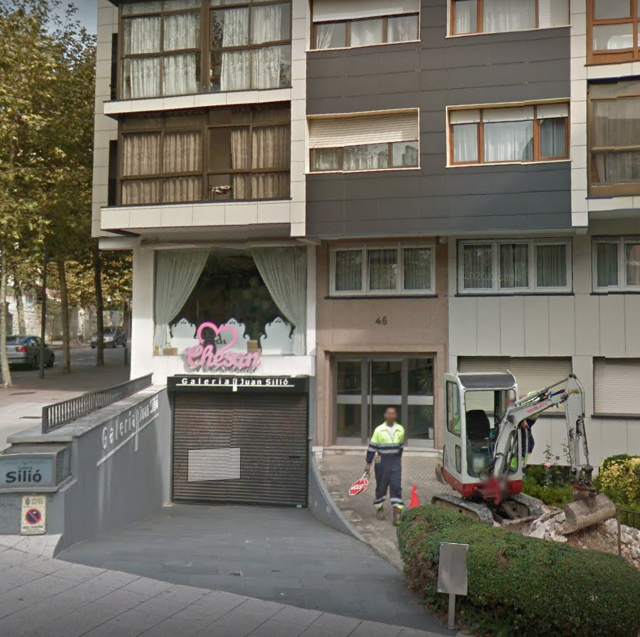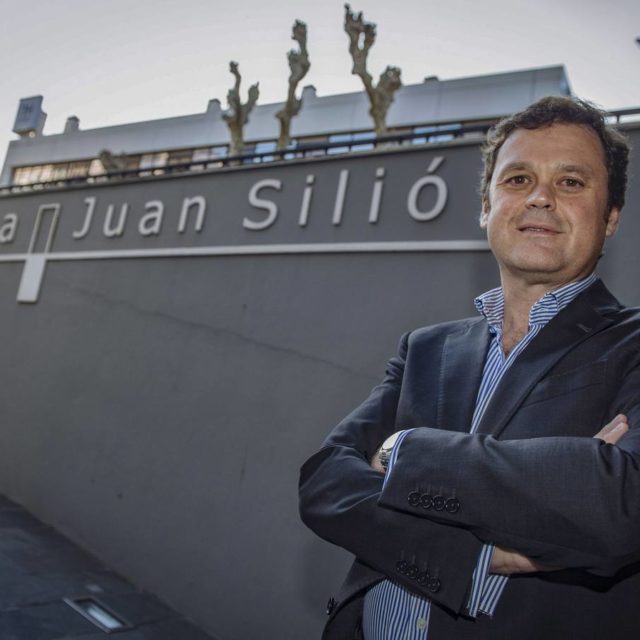
Letras de la Galería Juan Silió
Hace poco recogimos las 32 letras corpóreas (16 grandes en metal y 16 pequeñas en PVC) de la Galería Juan Silió, que fueron retiradas tras el cambio de imagen que se realizó el pasado año de la mano de Mutta Estudio.
Estas letras se instalaron en el año 2006 cuando se inauguró el local actual de la Calle Sol y que marcaba el nuevo nombre. La Galería, una de las más veteranas y reconocidas a nivel nacional e internacional, la fundó Fernando Silió en 1988. Desde 1999 es su hijo, Juan Silió quien está a cargo de la Galería hasta hoy, donde también desde el año pasado, tienen una nueva galería abierta en Madrid.
Ubicación de las letras en el rótulo antes del cambio (Foto: Google Maps)
Letras y logo del rótulo. (Foto: El Diario Montañés. Daniel Pedriza)